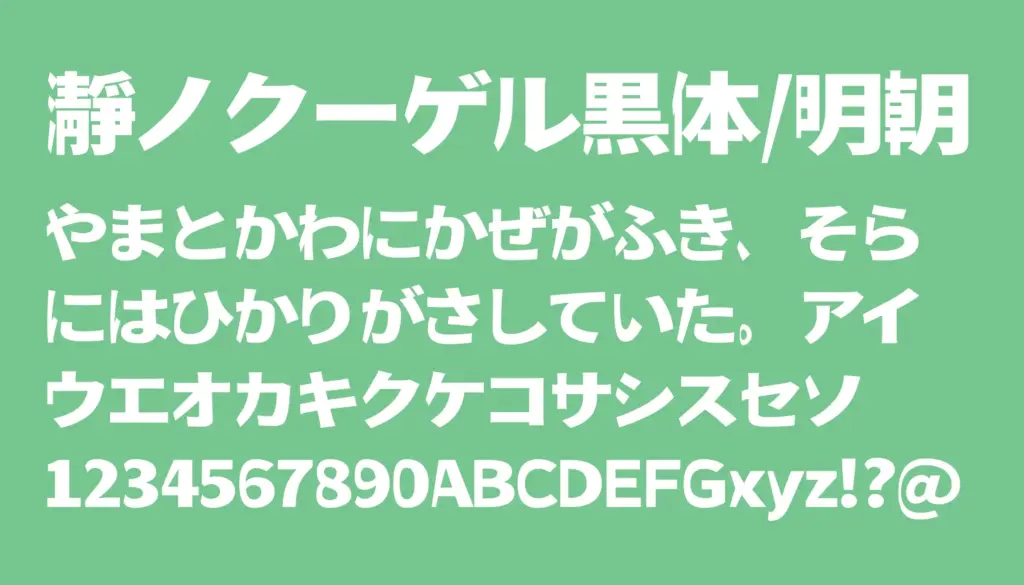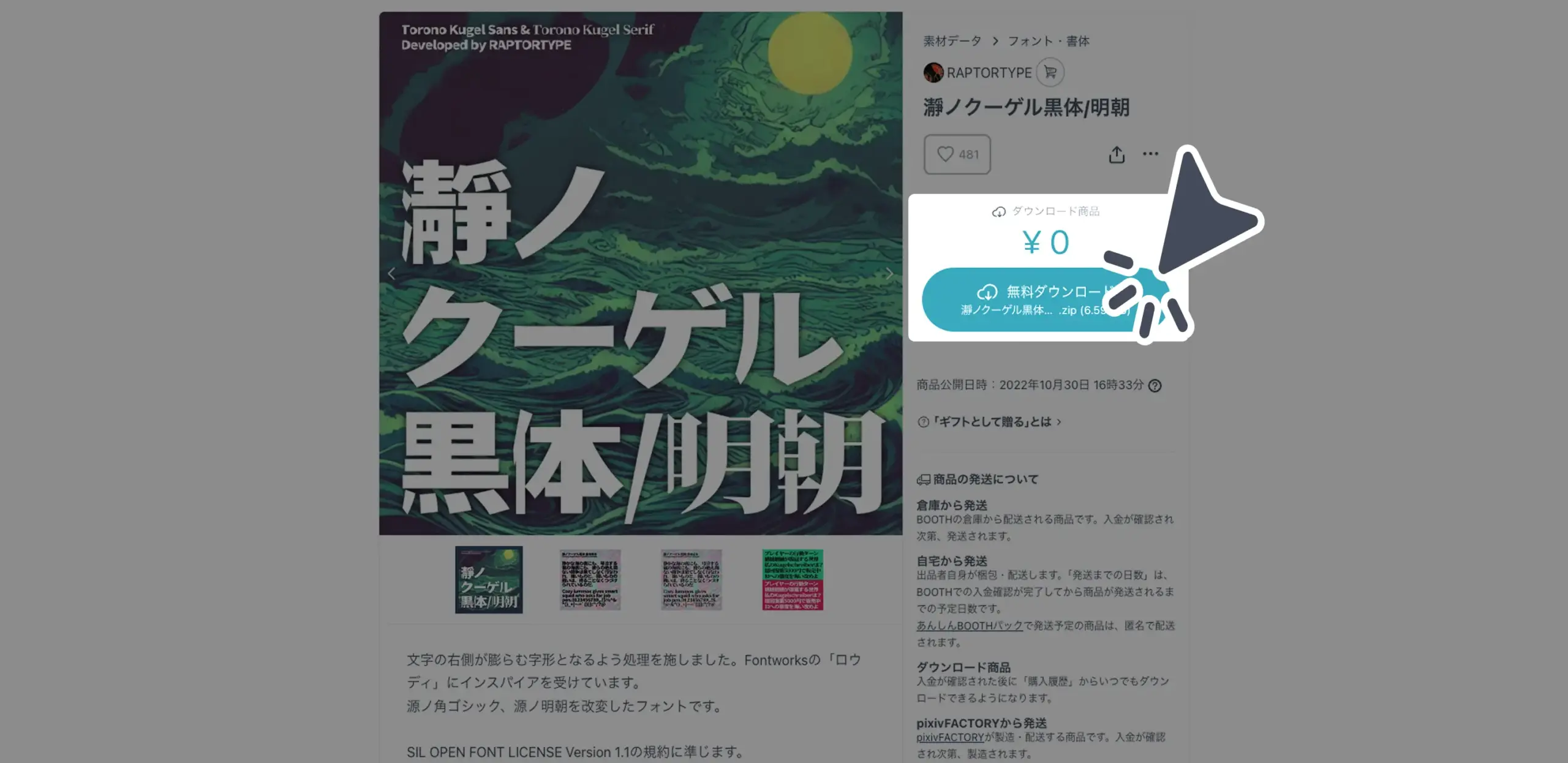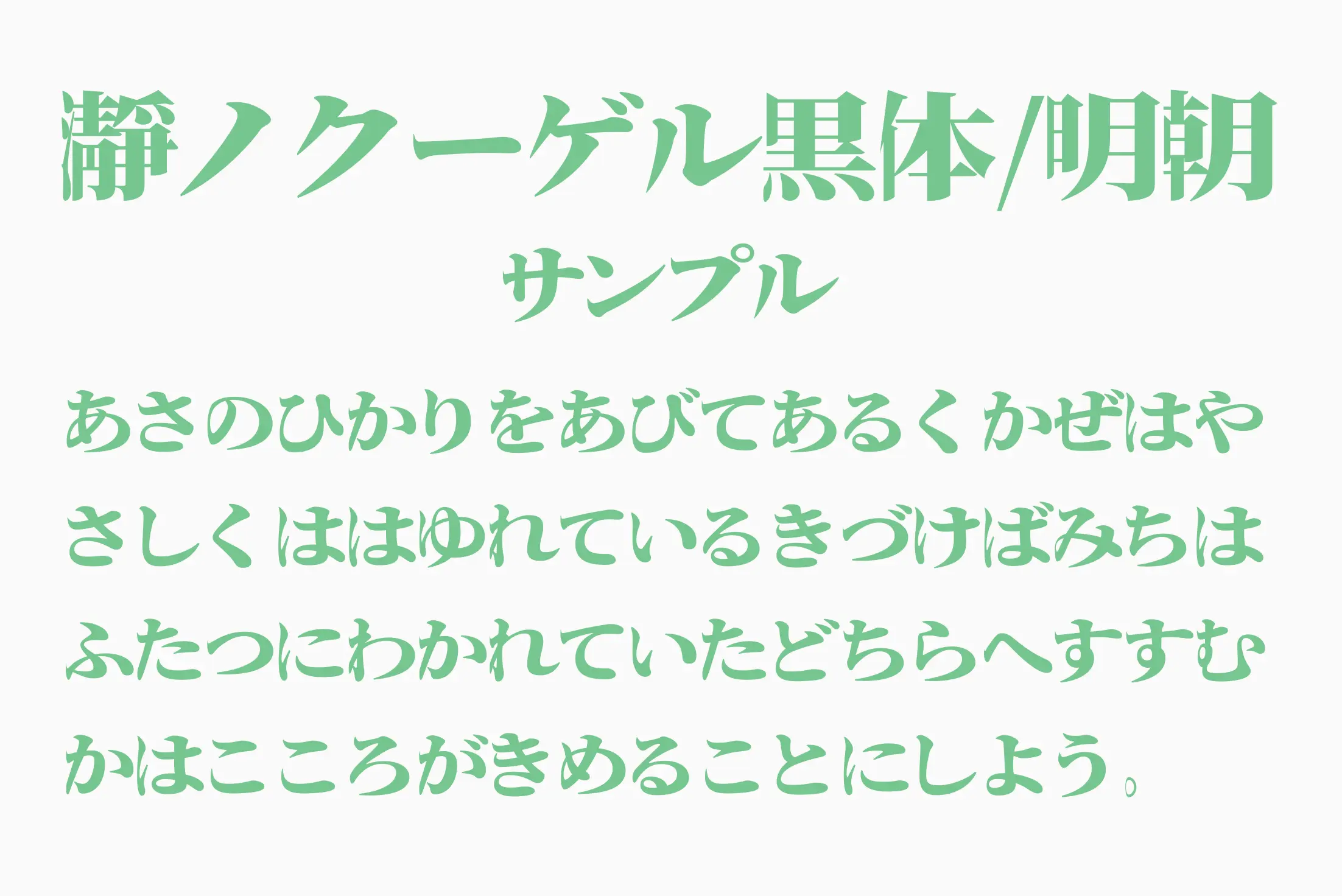
シンプルなゴシック体に柔らかさと気品を加えた、日本語と欧文どちらも対応するモダンなサンセリフフォントです。太字でありながら、角の取れた丸みと均整の取れた造形によって、視認性と親しみやすさの両立を実現。汎用性の高いフォントで、ビジネス資料からZINE・デザインワークまで幅広く活躍します。
瀞ノクーゲル黒体/明朝